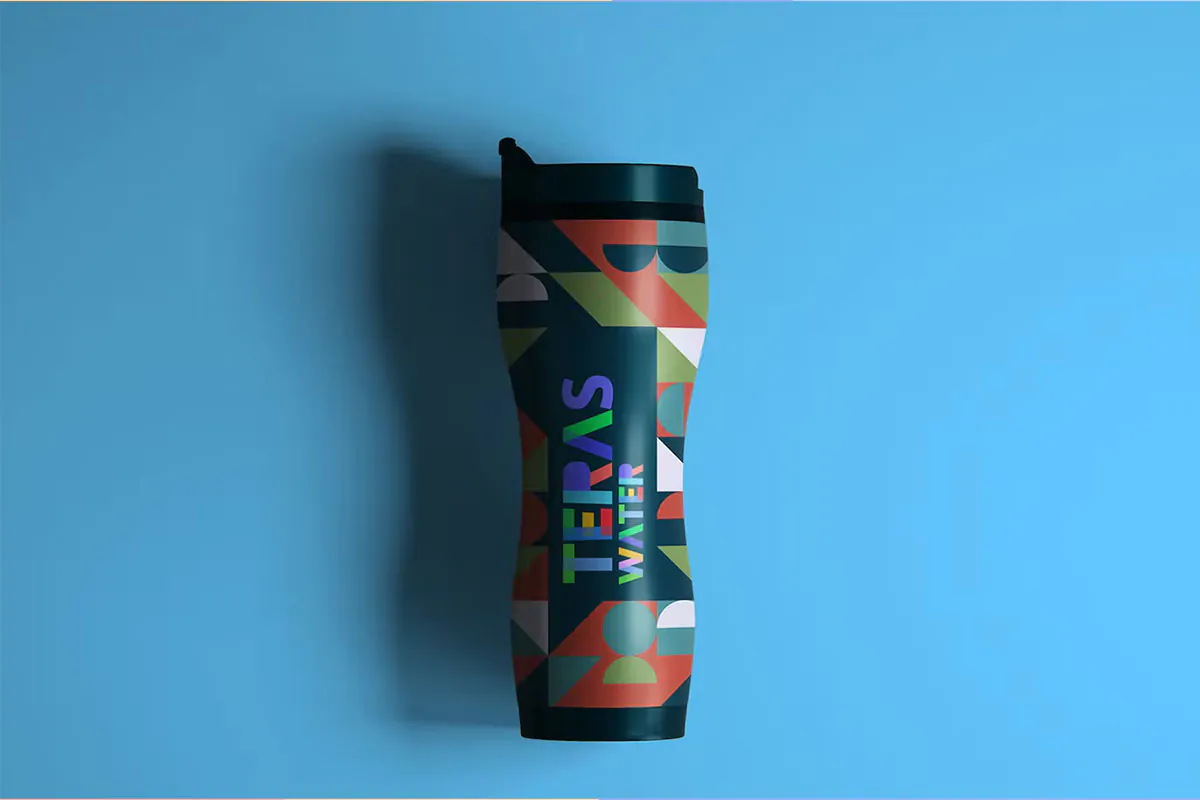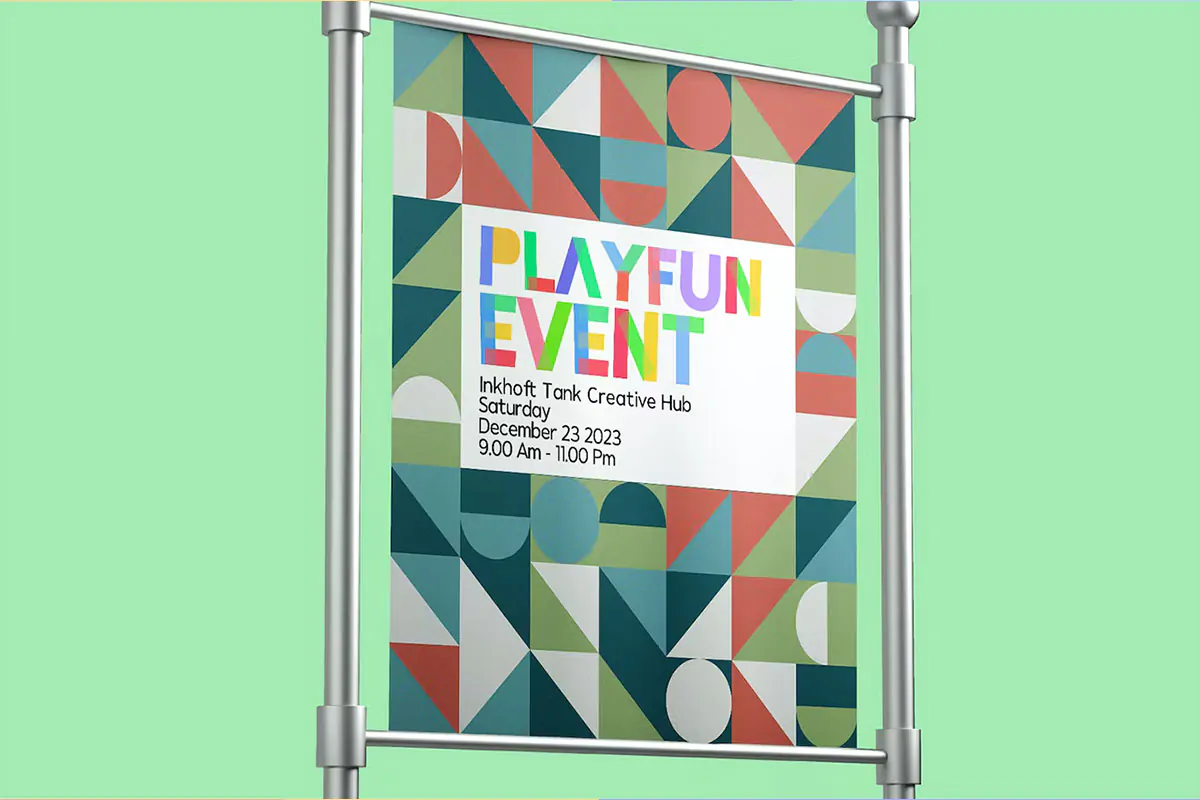
فونت رنگی کودکانه Playkita یک SVG فونت انگلیسی زیبا است که به سبک کودکانه طراحی شده است و مناسب برای استفاده در طراحی پوستر، بسته بندی محصولات، لوازم التحریر، ظروف یکبار مصرف و … میباشد.